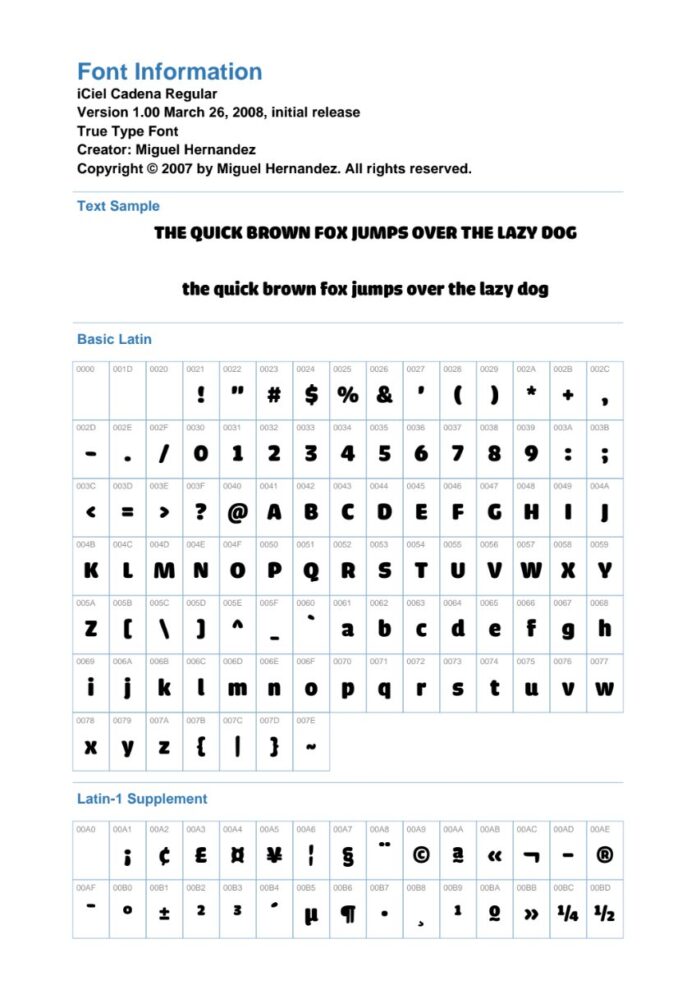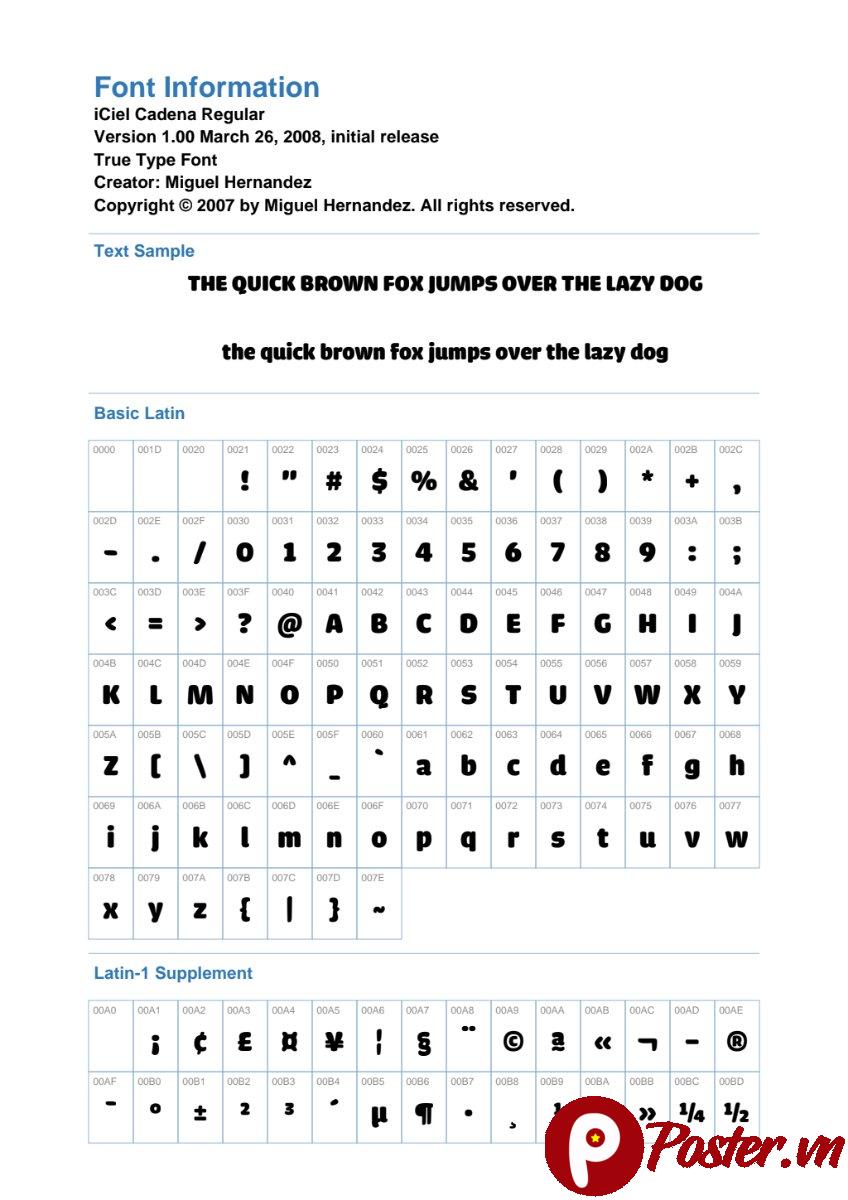
Trong thế giới thiết kế đồ họa, việc lựa chọn font chữ phù hợp có thể tạo nên sự khác biệt lớn cho một dự án. Font iCiel Cadena là một trong những lựa chọn nổi bật, mang đến sự kết hợp hoàn hảo giữa nét mạnh mẽ, hiện đại và tính dễ đọc. Được phát triển bởi iCiel, một trong những nhà cung cấp font chữ hàng đầu tại Việt Nam, Cadena nhanh chóng trở thành lựa chọn yêu thích của nhiều nhà thiết kế chuyên nghiệp.
Giới Thiệu Chung về Font iCiel Cadena
iCiel Cadena là một font chữ sans-serif đậm, được thiết kế với các đường nét rõ ràng và mạnh mẽ. Sự ra đời của Cadena đã mang đến một làn gió mới cho các dự án thiết kế, đặc biệt là những dự án cần sự nổi bật và cá tính. Font này không chỉ đẹp mắt mà còn rất linh hoạt, có thể ứng dụng trong nhiều ngữ cảnh khác nhau, từ tiêu đề báo chí, poster quảng cáo cho đến logo thương hiệu.
Đặc Điểm Nổi Bật của iCiel Cadena
- Thiết kế mạnh mẽ và hiện đại: Các ký tự của Cadena được thiết kế với độ dày đồng nhất, tạo cảm giác vững chãi và hiện đại. Điều này giúp font chữ dễ dàng thu hút sự chú ý và truyền tải thông điệp một cách rõ ràng.
- Tính dễ đọc cao: Mặc dù có độ đậm đặc trưng, iCiel Cadena vẫn đảm bảo tính dễ đọc tuyệt vời. Khoảng cách giữa các ký tự được căn chỉnh hợp lý, giúp người đọc dễ dàng nhận diện từng chữ cái và câu chữ.
- Đa dạng ứng dụng: Với phong cách độc đáo, Cadena phù hợp cho nhiều loại hình thiết kế. Bạn có thể sử dụng nó cho các tiêu đề lớn, slogan, bao bì sản phẩm, hay thậm chí là nội dung chính trong một số trường hợp đặc biệt.
- Hỗ trợ tiếng Việt: Đây là một điểm cộng lớn của iCiel Cadena, giúp các nhà thiết kế tại Việt Nam dễ dàng sử dụng mà không lo lỗi font hay thiếu ký tự đặc biệt.
Ứng Dụng của Font iCiel Cadena trong Thiết Kế
Với những ưu điểm vượt trội, font iCiel Cadena có thể được ứng dụng rộng rãi trong nhiều lĩnh vực thiết kế khác nhau:
Thiết Kế Quảng Cáo và Marketing
Trong lĩnh vực quảng cáo, việc tạo ra một thông điệp nổi bật là vô cùng quan trọng. iCiel Cadena với nét chữ đậm và hiện đại là lựa chọn lý tưởng cho các banner, poster, tờ rơi hay biển quảng cáo. Nó giúp thông điệp của bạn trở nên mạnh mẽ và dễ nhớ hơn. Poster.vn cung cấp các mẫu thiết kế sẵn có sử dụng font Cadena, giúp bạn tiết kiệm thời gian và công sức.
Thiết Kế Thương Hiệu và Logo
Một logo ấn tượng cần một font chữ độc đáo. iCiel Cadena có thể mang lại sự khác biệt cho logo của bạn, tạo nên một hình ảnh thương hiệu mạnh mẽ và chuyên nghiệp. Các doanh nghiệp muốn thể hiện sự năng động, hiện đại và đáng tin cậy sẽ tìm thấy Cadena là một công cụ đắc lực.
Thiết Kế Website và Ứng Dụng
Trong thiết kế giao diện người dùng (UI/UX), tính dễ đọc là yếu tố then chốt. iCiel Cadena có thể được sử dụng cho các tiêu đề, nút bấm hoặc các phần tử quan trọng khác trên website và ứng dụng, giúp người dùng dễ dàng tương tác và nắm bắt thông tin.
Thiết Kế Ấn Phẩm In Ấn
Từ bìa sách, tạp chí đến bao bì sản phẩm, iCiel Cadena đều có thể phát huy tối đa hiệu quả. Font chữ này giúp các ấn phẩm in ấn trở nên chuyên nghiệp, thu hút và dễ đọc, đặc biệt là khi sử dụng cho các tiêu đề hoặc thông tin quan trọng.